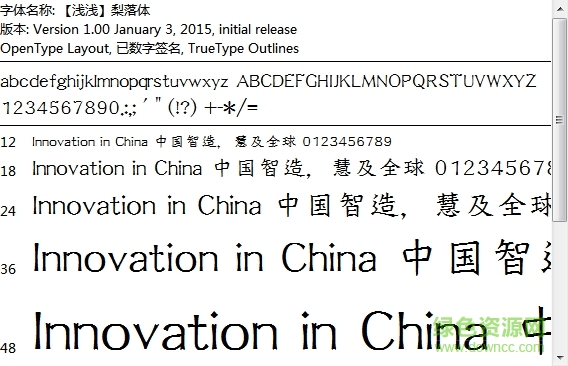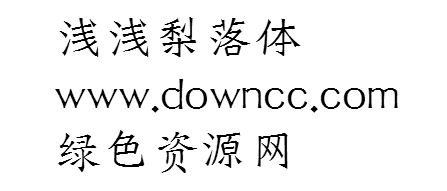
淺淺梨落字體
梨落體是淺淺美化后的中文字體,是在蘋果黑體STHeiti上美化而來,讓字體擁有不一樣的藝術(shù)效果,中文字跡很有楷書字體特色,如果你喜歡就來綠色資源網(wǎng)體驗(yàn)吧!
淺淺梨落體字體特色
愿有人陪你顛沛流離
如果沒有
愿你成為自己的太陽
梨落體有三種形態(tài),支持黑體韓語、黑體日本語和中文字體,中文均采用楷體書法字體特色,英文端正流暢,在標(biāo)點(diǎn)上采用了幾何圖案,細(xì)節(jié)細(xì)膩,討人喜歡。